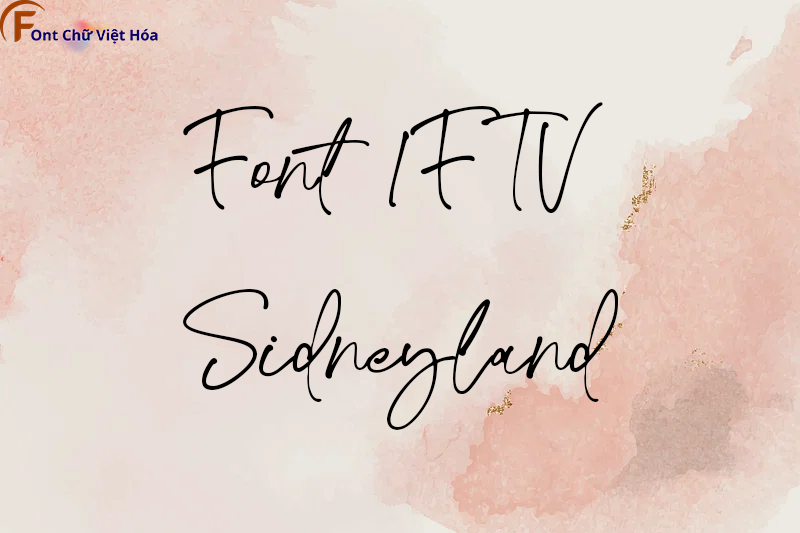
Font 1FTV Sidneyland
Phân loại: Độc đáo
Font 1FTV Sidneyland thuộc bộ Font 1FTV, đây là một lựa chọn hoàn hảo cho những ai đang tìm kiếm một kiểu chữ độc đáo và sáng tạo. Với phong cách chữ thanh lịch, mềm mại nhưng không kém phần hiện đại, font này không chỉ phù hợp cho các thiết kế in ấn, quảng cáo mà còn tạo nên điểm nhấn cho các dự án thương hiệu cá nhân. Ngoài ra, Font 1FTV Sidneyland còn hỗ trợ đa ngôn ngữ, giúp bạn linh hoạt trong việc sử dụng ở nhiều thị trường khác nhau. Hãy khám phá sức hút của font này để mang lại sự tinh tế và chuyên nghiệp cho thiết kế của bạn!